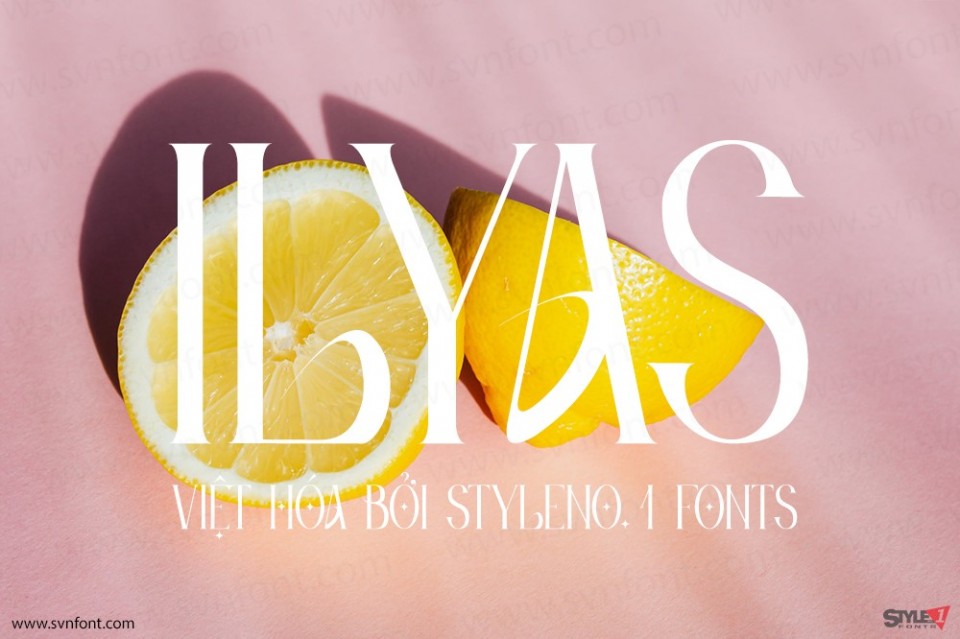
Font việt hóa SVN Ilyas
Trong thế giới đồ họa, việc tìm kiếm một bộ Font Miễn Phí chất lượng luôn là ưu tiên hàng đầu của các bạn học sinh và giáo viên. Font việt hóa SVN Ilyas nổi lên như một giải pháp tối ưu nhờ sự kết hợp giữa nét cổ điển serif và hơi thở hiện đại. Được chăm chút kỹ lưỡng về dấu tiếng Việt, bộ font này giúp mọi văn bản trở nên chuyên nghiệp, thanh lịch và vô cùng dễ đọc trên nhiều thiết bị khác nhau.
Ưu điểm nổi bật của Font việt hóa SVN Ilyas
Thiết kế tinh tế và tính ứng dụng cao
Font việt hóa SVN Ilyas sở hữu những đường nét mảnh mai nhưng chắc chắn, tạo cảm giác tin cậy cho người xem. Đối với các bạn học sinh, đây là lựa chọn tuyệt vời để trình bày bài thuyết trình hoặc làm báo tường kỹ thuật số. Font chữ này không chỉ đẹp mắt mà còn hỗ trợ đầy đủ bộ gõ tiếng Việt, giúp loại bỏ hoàn toàn lỗi hiển thị ký tự lạ hay mất dấu thường gặp ở các bộ font nước ngoài.
Phù hợp cho nhiều mục đích giáo dục
Các thầy cô giáo có thể sử dụng SVN Ilyas để thiết kế giáo án điện tử hoặc tài liệu học tập sinh động. Nhờ cấu trúc chữ rõ ràng, học sinh sẽ dễ dàng tiếp nhận thông tin mà không bị mỏi mắt. Ngoài ra, tính thẩm mỹ cao của nó còn giúp các sản phẩm sáng tạo của nhà trường thêm phần ấn tượng và chuyên nghiệp hơn trong mắt phụ huynh.
Cách sử dụng Font việt hóa SVN Ilyas hiệu quả
Để phát huy tối đa vẻ đẹp của Font việt hóa SVN Ilyas, bạn nên kết hợp nó với các tông màu trung tính hoặc pastel nhẹ nhàng. Việc điều chỉnh khoảng cách dòng và kích thước chữ hợp lý sẽ giúp bố cục trang giấy hoặc slide bài giảng trở nên thoáng đãng. Hãy thử áp dụng bộ font này ngay hôm nay để trải nghiệm sự khác biệt trong từng nét chữ. Chúc các bạn có những tác phẩm thiết kế thật ưng ý với nguồn Font Miễn Phí, Font Việt Hóa, Font việt hóa SVN Ilyas chất lượng này.